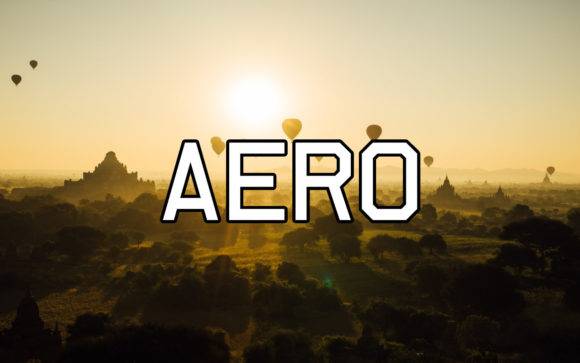
Fuente Aero para manualidades, logotipos y proyectos de impresión
Esta fuente sans-serif contemporánea, diseñada para brindar claridad y velocidad visual, ofrece curvas suaves y bordes definidos, lo que la hace perfecta para manualidades, logotipos y diseños de impresión donde la estética moderna es fundamental.
Como fuente, Aero aporta un toque futurista y elegante a cualquier proyecto, ofreciendo precisión en los archivos de corte y elegancia en los formatos de impresión. Su versatilidad conecta la imagen de marca con tecnología de vanguardia y la artesanía minimalista y depurada.
Ya sea que esté creando etiquetas de productos, monogramas o regalos personalizados, Aero proporciona un acabado profesional con alta legibilidad.
- Diseño geométrico moderno con líneas limpias.
- Perfecto para cortar e imprimir con precisión.
- Altamente legible en todos los tamaños y formatos.
- Elegante y profesional para la marca.
P: ¿Qué estilo tiene la fuente Aero?
A: Aero es una fuente sans-serif moderna que presenta curvas estilizadas y formas de letras minimalistas para trabajos de diseño limpios.
P: ¿Se imprime bien en formatos grandes?
R: Por supuesto. Aero conserva su forma y legibilidad tanto en impresiones de pequeña como de gran escala.
P: ¿Para qué tipo de proyectos es más adecuado Aero?
R: Es ideal para marcas elegantes, proyectos de máquinas de corte, materiales promocionales y diseños minimalistas.